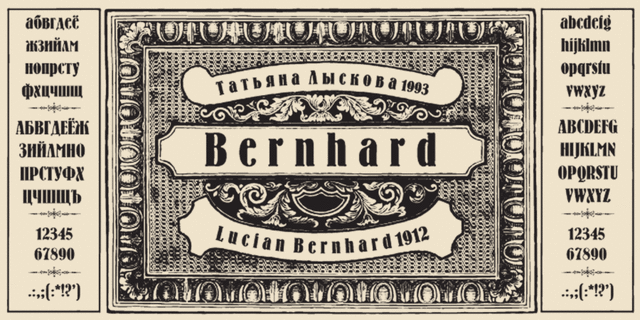
Шрифт разработан в фирме ПараТайп (ПараГраф) в 1993 (дизайнер Татьяна Лыскова) на основе рисунков шрифта Bernhard Condensed фирмы Bauersche GieЯerei, 1912 (дизайнер Люциан Бернхард). Предназначен для применения в рекламе и акциденции.